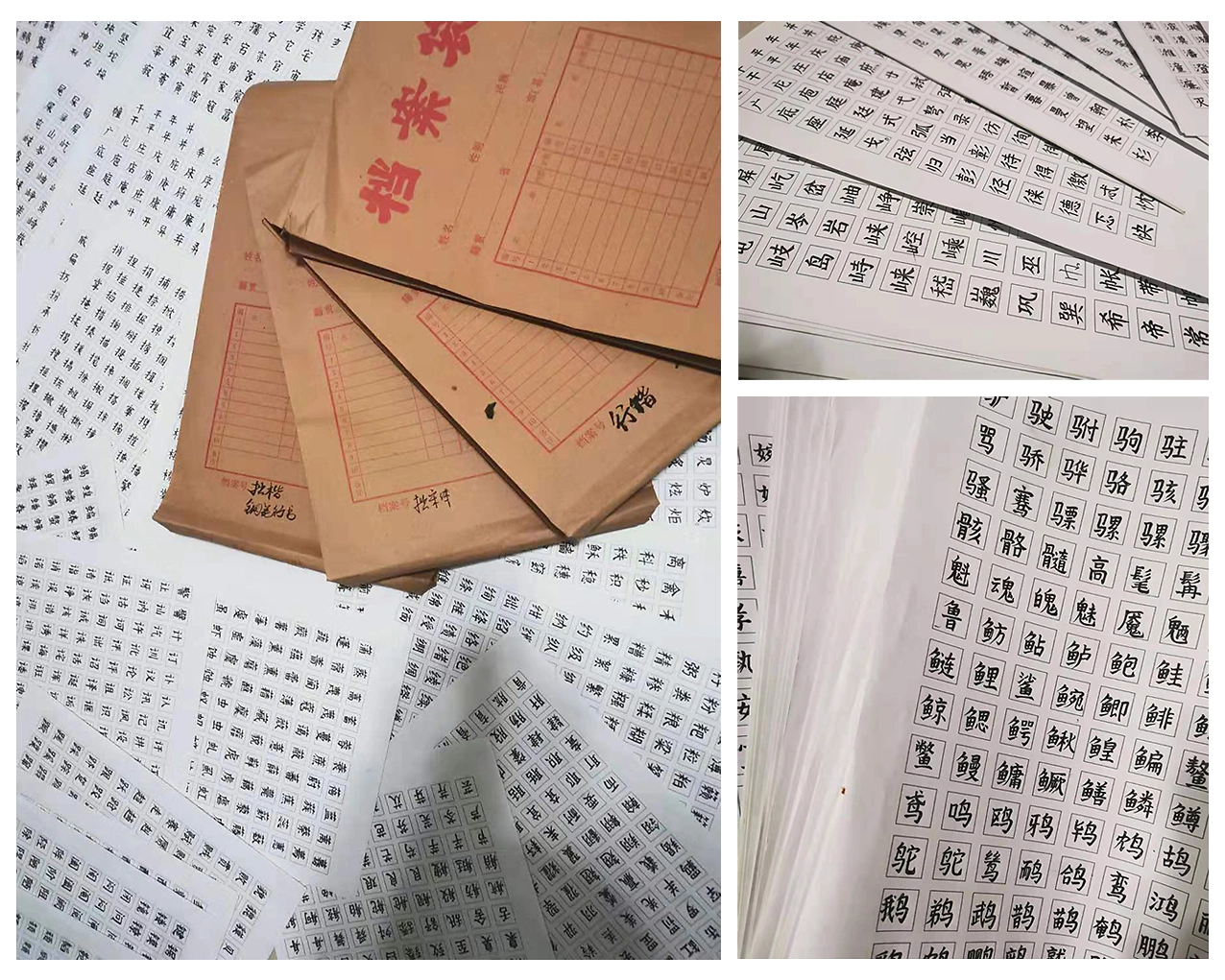
江西拙楷
字体简介
“江西拙楷”是一款由字体设计师黄煜臣独立创作的手写楷体字体,最初版本于2020年元旦发布。这款字体以手写风格为特色,笔画带有书写的自然痕迹,相比标准化的电脑楷体,它的字形不够规整,每个字的笔画粗细和结构都不完全统一,呈现出一种朴拙而自然的质感。它包含6763个汉字,符合GB2312字符集,支持简体中文、基本拉丁文和常用符号,适用于多种设计场景。
江西拙楷的设计过程耗时半年,从手稿到最终成品,黄煜臣花费大量精力调整细节,比如调节点就用了20多天。字体以设计师家乡“江西”命名,既是对外分享的免费字体,也是对家乡文化的宣传。